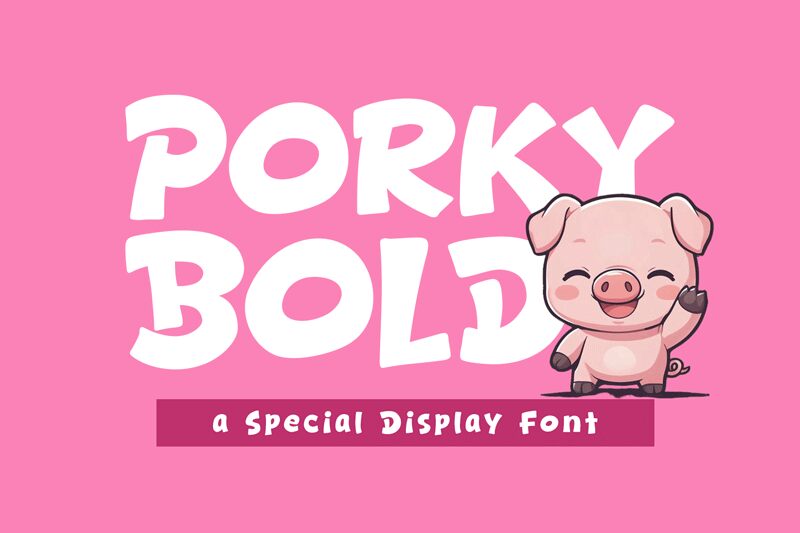
Porky Bold, por Khurasan & Jalembe, é uma fonte gratuita estilo cartoon com uma atitude saltitante e desenhada à mão. As letras parecem robustas e divertidas, com curvas suaves e irregulares e pequenas inclinações que conferem ao conjunto da palavra uma sensação de movimento, fugindo do aspecto estático.
É perfeita para embalagens de snacks, capas de livros infantis, títulos no estilo banda desenhada, panfletos de eventos e esboços de logotipos alegres onde uma fonte gratuita precisa de ser marcante e amigável desde a primeira palavra. Como as formas são amplas, gordinhas e um pouco irreverentes, Porky Bold funciona especialmente bem para títulos curtos, chamadas de capa e marcas rápidas que precisam de um toque caloroso e divertido, em vez de um acabamento polido.